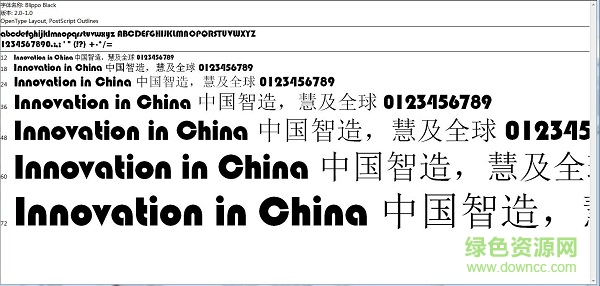
blippobt black字體是一款字型粗壯渾厚的英文字體,折筆處呈圓弧形,剛?cè)岵?jì),通透美觀,整體結(jié)構(gòu)協(xié)調(diào)好看,適用于標(biāo)題或是影視海報(bào)設(shè)計(jì),喜歡的朋友快來下載吧!
具有字面飽滿等特點(diǎn),筆畫厚重飽滿,除了適用于傳統(tǒng)印刷媒介的各類標(biāo)題與正文排版,還適用于屏幕顯示、廣告標(biāo)語和包裝設(shè)計(jì)。